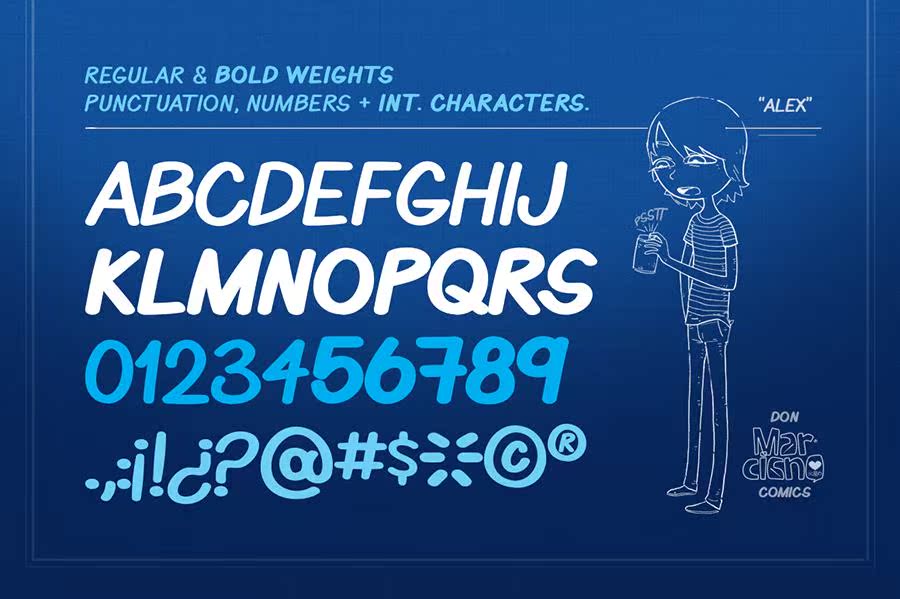
Benjacomicbookfreefont是为ComicDialogue创建的字体。该字体最初是为称为Jemandrill的网络喜剧系列设计的。该字体采用了Love and Care的两种样式,即Regular和Bold,这两种样式在对话框Bubbles中共同创建了一个动态流。因此,从Fund和Endaring Comics系列的边框、颜色和对话框层,ComeSimpleyeetstTylisticTypeFacewhat want to the story,you want to tell。